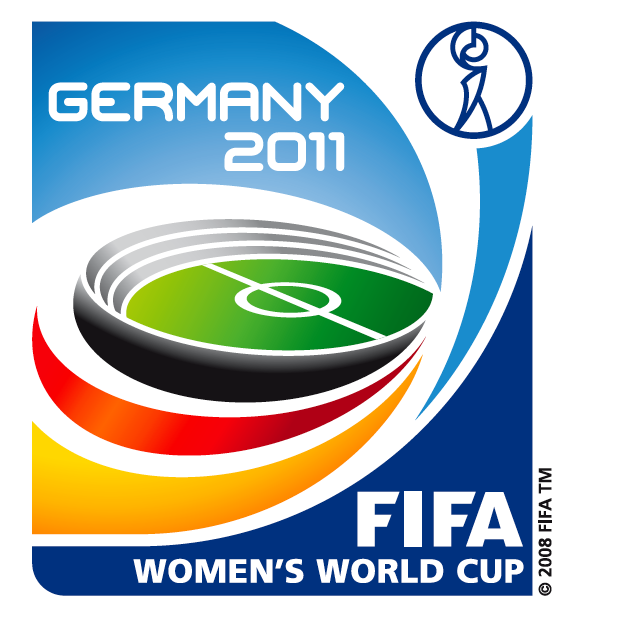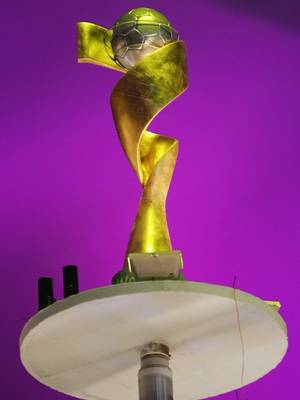
Wettbewerb zur Plakatgestaltung
Auch, wenn ich befangen bin, finde ich die Wettbewerbsbedingungen ausgesprochen fair, was bei Designwettbewerben keine Selbstverständlichkeit ist. Viele Grüße ins Forum
Der Wettbewerbsinhalt:
Im kommenden Jahr findet vom 26. Juni bis 17. Juli in Deutschland die FIFA Frauenweltmeisterschaft™ statt. Das Motto: »20ELF von seiner schönsten Seite«. Das Organisationskomitee FIFA WM 2011 lädt aus diesem Anlass in Kooperation mit dem BDG Berufsverband der Deutschen Kommunikationsdesigner e.V. alle professionellen Designer sowie Designstudenten zur Teilnahme an einem Wettbewerb für die Gestaltung des offiziellen Posters ein. Das Poster wird der Öffentlichkeit zur Endrundenauslosung am 29. 11. 2010 präsentiert und von diesem Zeitpunkt an als zusätzliches Werbe- und Imagemedium eingesetzt.
Der BDG hat eine Fachjury zusammengestellt, die aus allen Einsendungen zehn bis fünfzehn Entwürfe vorauswählt, die der Jury zur Beurteilung vorgelegt werden. Die Jury setzt sich zu gleichen Teilen aus den BDG-Fachjuroren und den Repräsentanten des DFB/OK zusammen. Sie wählt die besten drei bis fünf Entwürfe aus, die dann zur öffentlichen Abstimmung auf die Website des DFB und/oder auf die Website eines Medienpartners gestellt werden.
Die Fachjury setzt sich zusammen aus der Designerin Verena Gerlach, dem BDG-Präsidenten und Typografen Henning Krause, der Dozentin für Typografie und Bildgestaltung Mariko Takagi und Florian Pfeffer, Professor für Kommunikationsdesign an der Staatlichen Hochschule für Gestaltung Karlsruhe. Vier noch nicht benannte Mitglieder des DFB/OK vervollständigen die achtköpfige Jury.
Könnte jemand, der die Frutiger hat, die benötigten zwei Textzeilen* in verschiedenen Schnitten setzen? Ich hab sie nicht, und mit einer PDF- oder EPS-Datei mit dem in Pfade umgewandelten Text könnte ich da mal experimentieren ohne sie klauen zu müssen. ;)
* „FIFA Women’s World Cup Germany 2011“ und „26 June – 17 July 2011“
Ist dieses Plakat von dir, Christian?
Wenn ja, könntest du mir erklären was genau das runde etwas in der oberen rechten Ecke darstellen soll?
:hammer: der ist gut. Das ist das offizielle WM-Logo im allerbesten DFB-Design, geht aber locker als Plakat durch.
… das runde etwas in der oberen rechten Ecke darstellen soll?
Das ist der stilisierte Pokal.
Hier in echt:
Soso, das soll der Pokal sein, naja selbst jetzt wo ich den Pokal kenne fällt es mir schwer ihn in diesem etwas zu erkennen, ein Fussball wäre vielleicht ohnehin angebrachter gewesen...
Mich stört auf dem Plakat die Diskrepanz zwischen dem relativ breiten "20" und dem schmalen "11". Nachdem ich "20ELF" gelesen habe, denke ich mir aber, dass dies vielleicht auch gerade so gewollt ist.